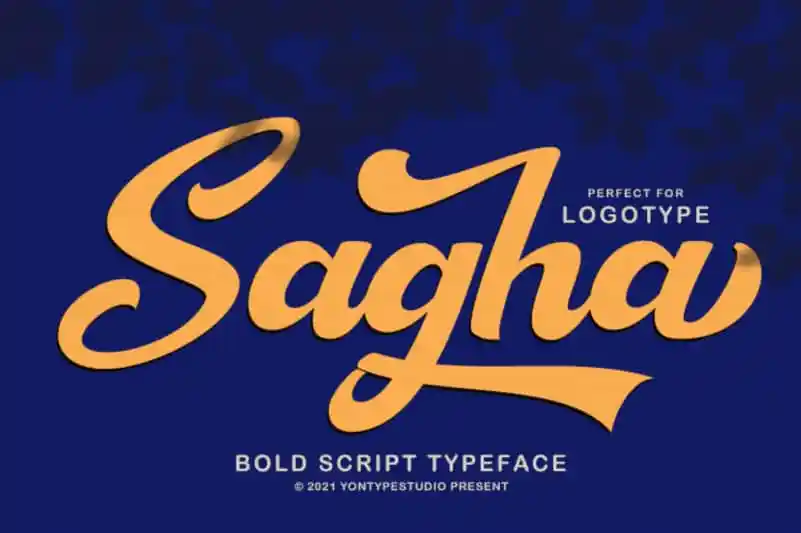
Sagha Script Font – Fonte Grátis
Sagha Script Font
Introduzimos Sagha Script Font – uma tipografia script multiformente que inclui muitas alternativas diferentes para cada minúscula. Esta fonte oferece a você um verdadeiro swiss army knife na sua biblioteca de fontes, permitindo que você personalize cada palavra à sua conveniência. É extremamente divertido e prático usar esta tipografia. Sagha Script é perfeitamente adequada para logotipos e designs de roupas, bem como ideia perfeita para criação de impressões ou mercadorias. Seu uso não só permite que você use as qualidades artísticas das formas para criar arte, mas também permite a você explorar o design gráfico dos objetos em um nível ainda mais profundo. Ainda não sabemos quanto isso vai mudar sua maneira de trabalhar com fontes script.